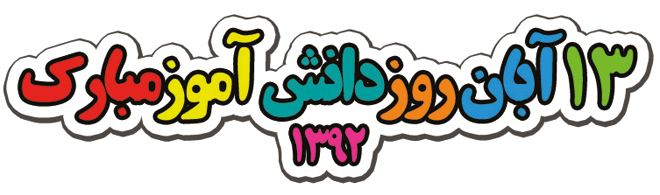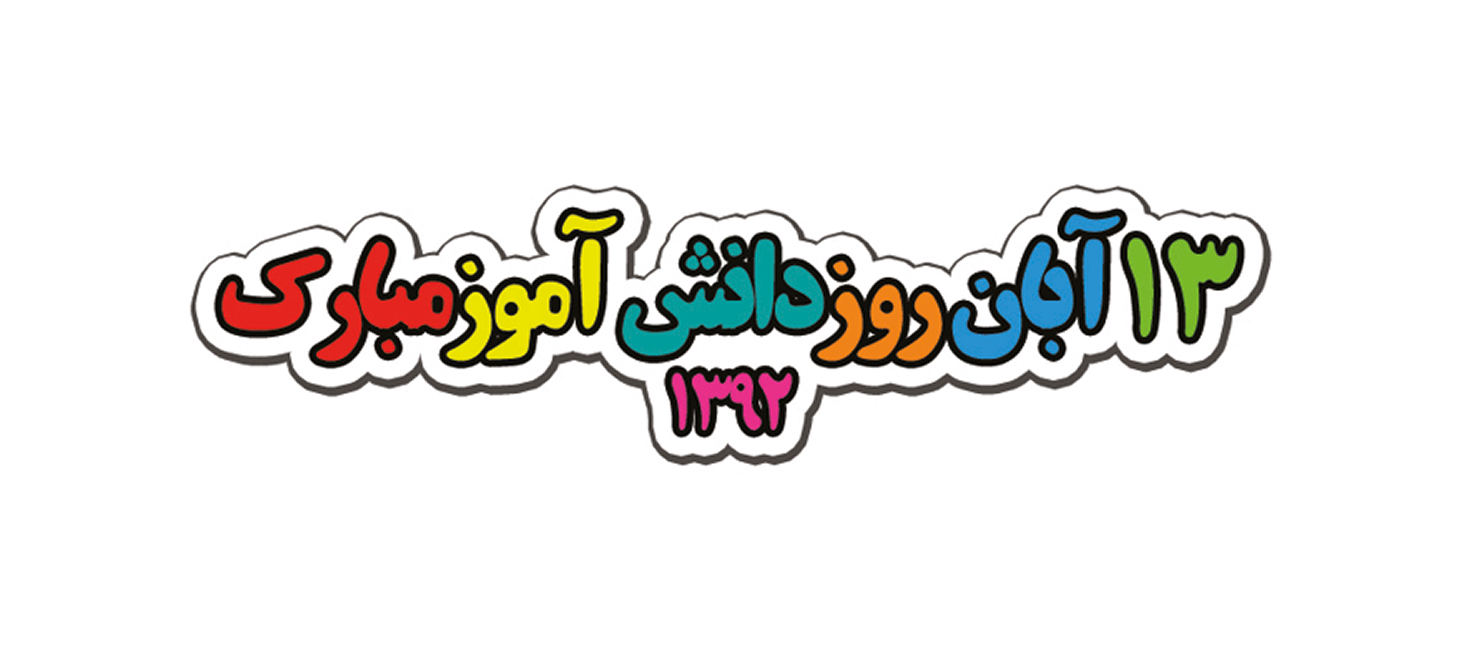
این فونت به لحاظ نرم افزاری ساختار ساده ای دارد و بیشتر مناسب استفاده در زمینه کارهای گرافیک ثابت است.
مهارت و خلاقیت شما در تنظیم دستی چیدمان حروف و رنگ بندی مناسب می تواند در زیبایی بیشتر این فونت موثر باشد.